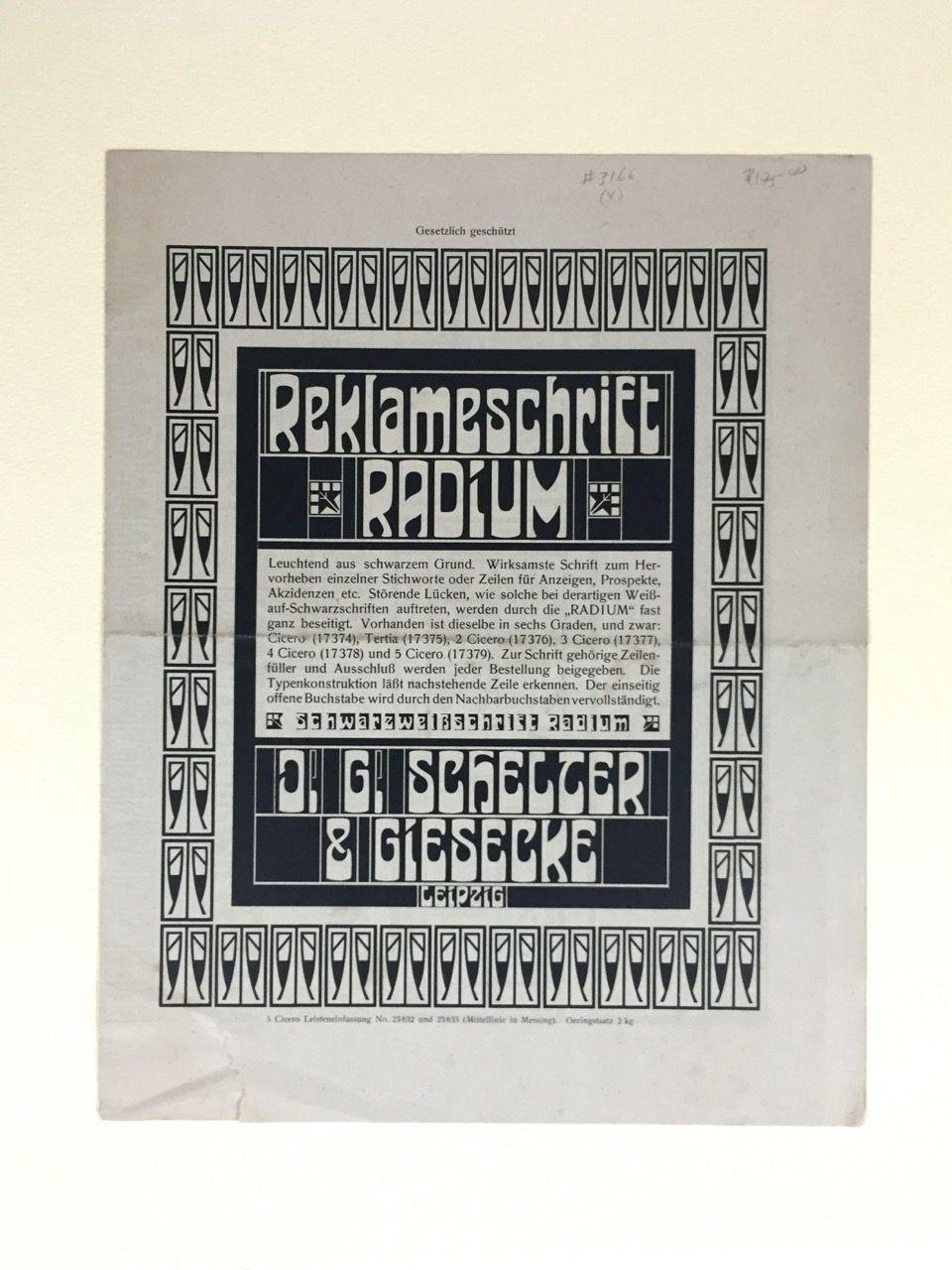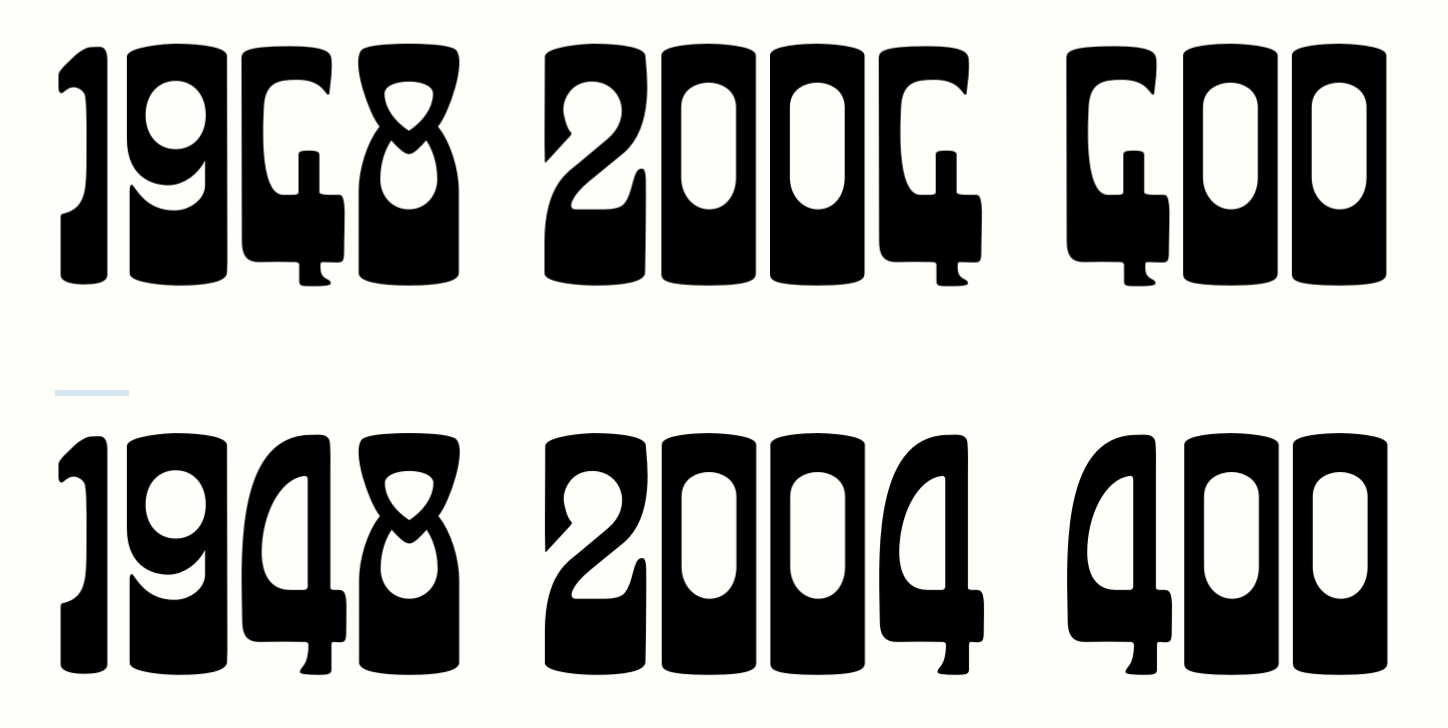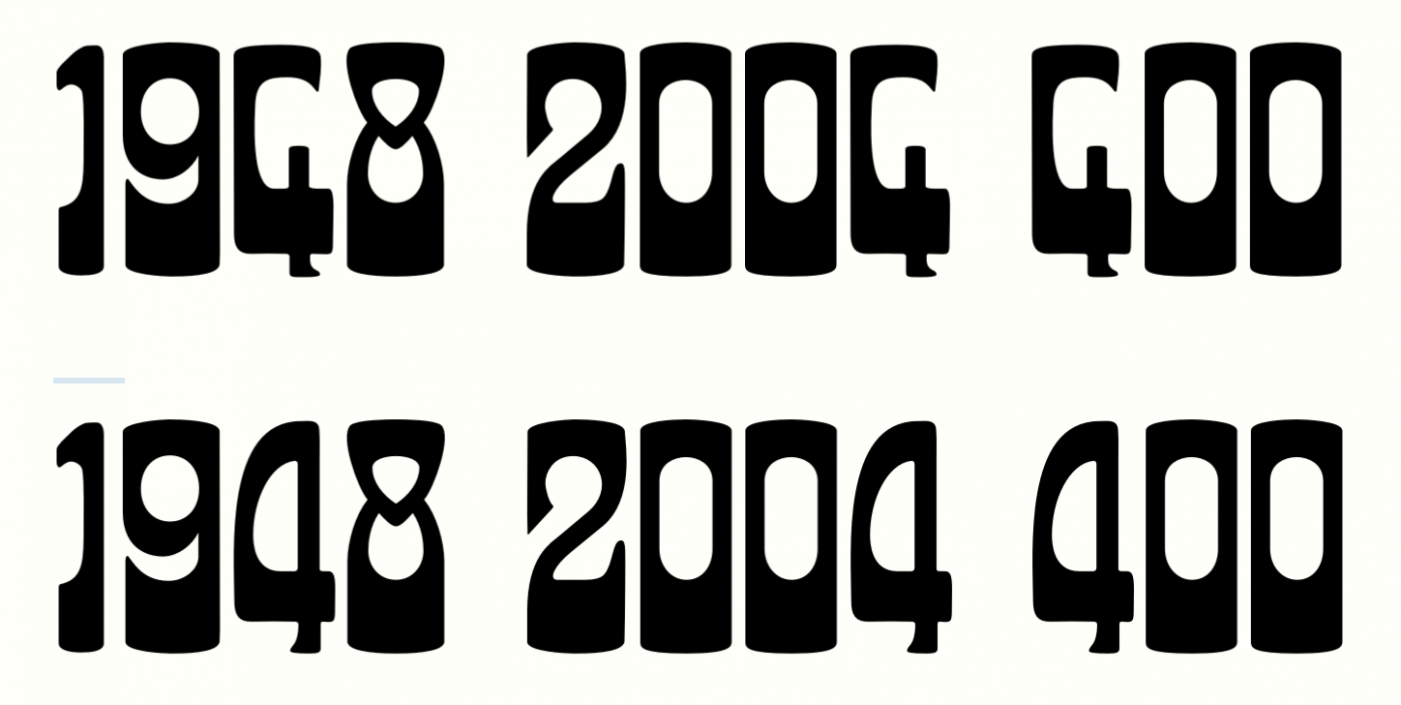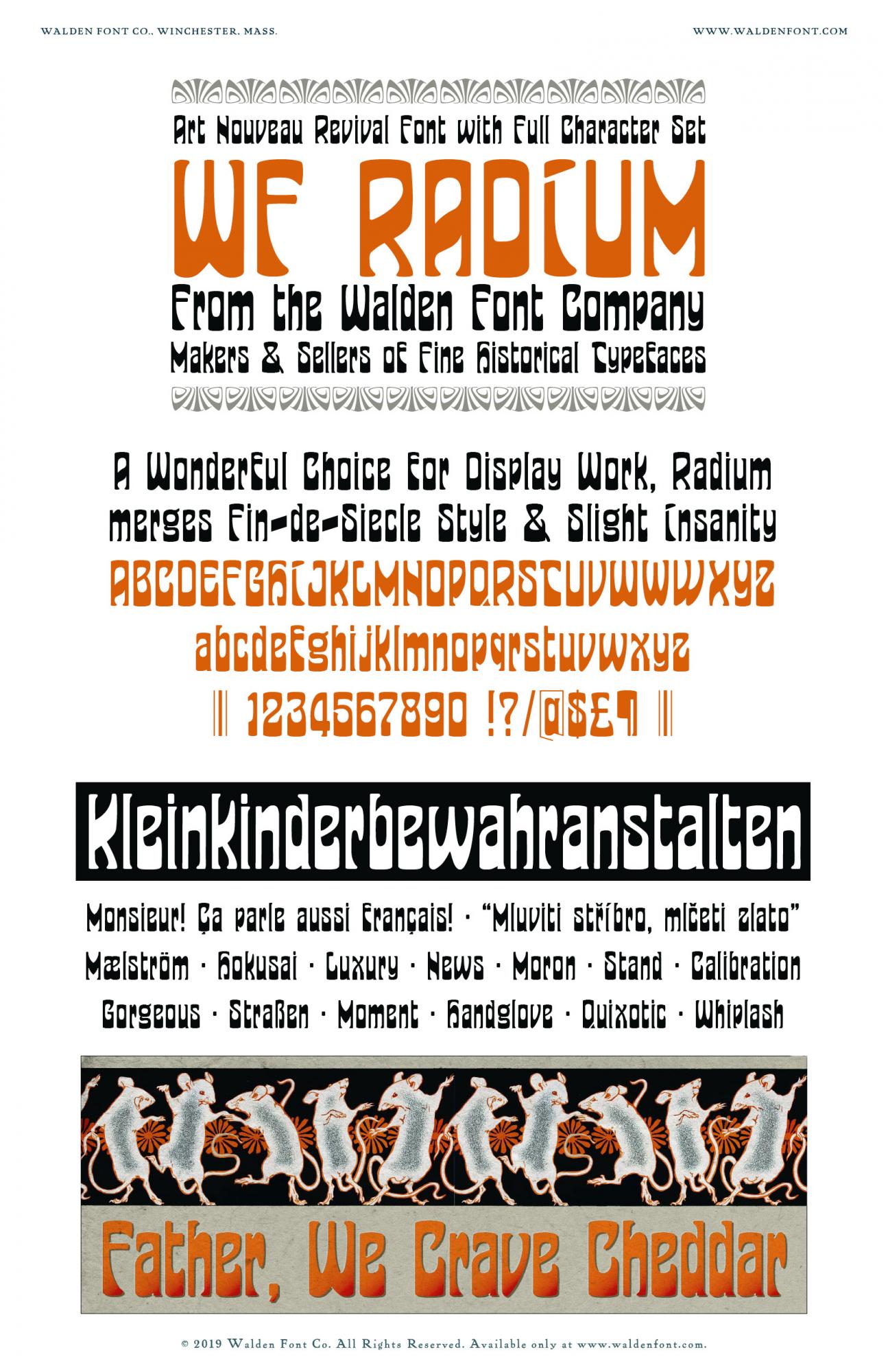
Suche Proben oder Anwendungsbeispiele der Radium von Schelter & Giesecke?
Für mich ist die 3. 4 die radiumigste, vielleicht ja den Querbalken noch deutlich fetter, oder auch geschlossen:
Diese beiden Varianten habe ich auch versucht. Die linke gefällt mir als solche, nur beim Lesen wird da immer ein G daraus. Die rechte ist links oben zu schwer, deshalb habe ich sie abgerundet und bin so auf der jetzigen Form gelandet.
Das wir den gleichen Gedankengang verfolgten beweist die Existenz der konvergierenden Evolution!
Ich finde lustig, wie viele Assoziationen die Zahlen bieten: die 1 guckt für mich schüchtern, die 8 eingeschnappt, die lachende 9 macht gute Laune, die Schwanen-2 sieht elegant aus. Wenn ich mich bei der 4 für eine Variante entscheiden müsste, würde ich wohl die Sägeblattvariante der Schraubzwingenvariante vorziehen :-|
Pfeffermühle? :twisted:
Na macht man sich auch so über anderer Leute Ziffern lustig?
Ich mach und tu, und am Ende wird mir meine schöne Acht verunglimpft!
Robert, vielen Dank dafür! Da muß ich also nochmal ran!
Das original-T ist besser als meines, auch das I paßt besser. Aber mit dem original-J kann ich mich nicht anfreunden, ich stelle es mal als extra-Glyphe dazu. Auch die Ornamente sind schick!